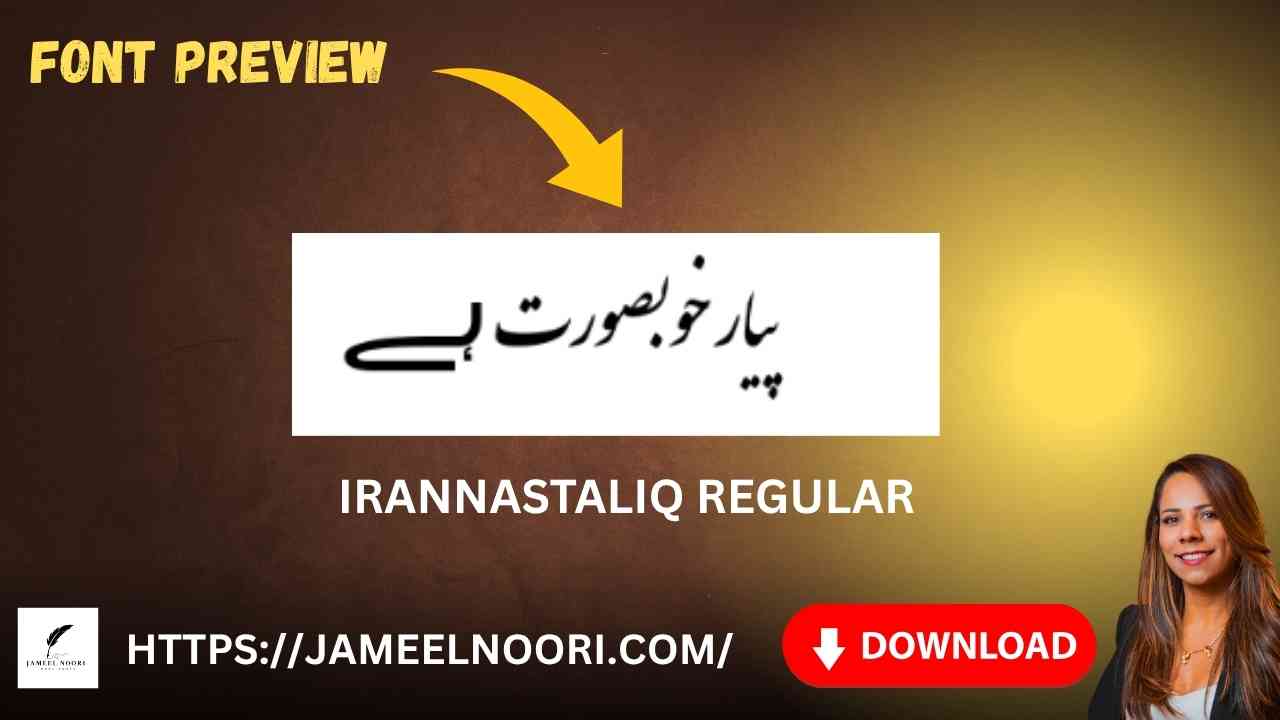
Download Urdu font IranNastaliq Regular – Complete Guide
Introduction – Download Urdu font IranNastaliq Regular
Agar aap Urdu ke khoobsurat Nastaliq style mein likhne ke shaukeen hain, to aap ke liye Download Urdu font IranNastaliq Regular ek perfect choice hai. Ye font na sirf aesthetically pleasing hai balkay Urdu calligraphy ko digital duniya mein zabardast taur pe represent karta hai. Is article mein hum detail se batayenge ke aap kaise isay download aur install kar sakte hain — wo bhi bilkul free!
What Is Download Urdu font IranNastaliq Regular
IranNastaliq Regular aik mashhoor TrueType Urdu font hai jo specially Persian aur Urdu calligraphy lovers ke liye design kiya gaya hai. Ye font traditional Nastaliq style ko modern typography ke sath combine karta hai.
Font Ki Key Features:
• Stylish aur readable Nastaliq style
Best Ways to Use IranNastaliq Regular Font
Ye font kai mukhtalif platforms aur applications mein use ho sakta hai. Neeche kuch mashhoor usage scenarios diye gaye hain:
Use Cases:
• Urdu novels ya books ke layout mein
• InPage Urdu software ke design projects mein
• YouTube Urdu thumbnails aur Islamic calligraphy mein
• Wedding Cards aur Digital Posters banane mein
Pakistan ke designers aur Urdu bloggers ke darmiyan ye font is liye mashhoor hai kyun ke:
• Iska style aesthetic aur readable hai
• Ye Urdu aur Persian dono languages ko support karta hai
Conclusion: Download Urdu font IranNastaliq Regular
Agar aap Urdu typing ya design projects mein classic aur readable Nastaliq look lana chahte hain, to Download Urdu font IranNastaliq Regular aaj hi karein. Iska use kar ke aap apne documents aur designs mein ek premium aur professional touch laa sakte hain — wo bhi bilkul free!
Is this font suitable for web design?
Not recommended for websites directly, but great for designing images or banners in Urdu.